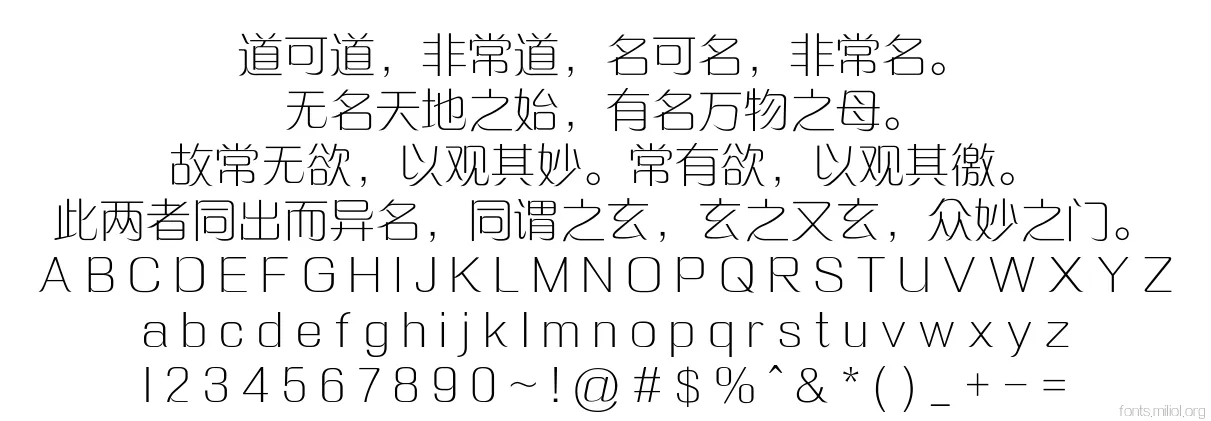
方正细倩_GBK (FZXiQian-M15) (FZXQK--GBK1-0) 字体下载
## 方正细倩_GBK:一款典雅纤细的中文字体
方正细倩_GBK(FZXiQian-M15)是方正字库推出的一款极具特色的中文字体,其设计灵感源自传统书法艺术与现代排版需求的完美结合。这款字体采用GBK编码标准,支持包括简体中文、繁体中文在内的20902个汉字字符,能够满足各类专业排版需求。
字体最显著的特点是笔画纤细优雅,横竖比例协调,转折处圆润流畅,整体呈现出清新脱俗的视觉效果。其15级字重的设计使字体在保持纤细特质的同时,依然保证了良好的可读性,特别适合用于时尚杂志、文艺书籍、产品包装等需要展现精致感的场合。
作为方正倩体系列的一员,细倩体延续了该系列温婉灵动的风格特征,但通过调整笔画粗细和结构比例,形成了独特的视觉语言。其GBK编码版本更是扩展了应用范围,使其成为设计师处理多语言文字排版时的理想选择。这款字体既传承了中文书法的美学精髓,又符合现代数字排版的实用需求,展现了中文字体设计的独特魅力。